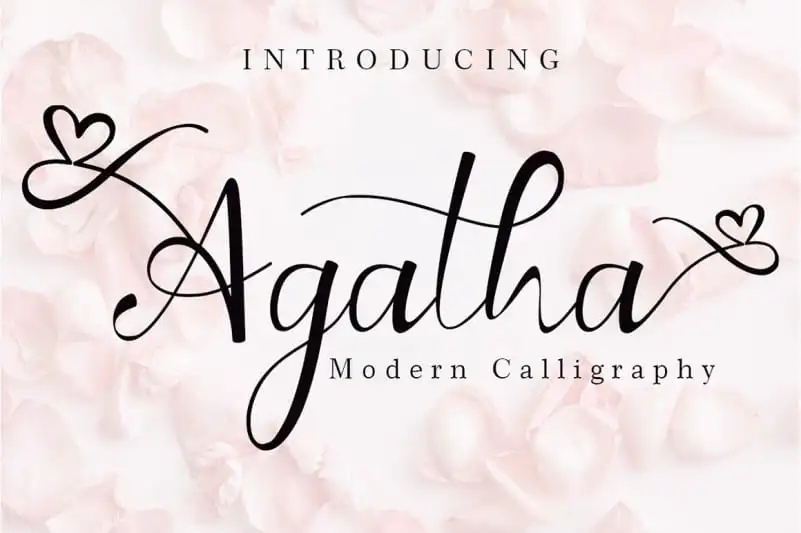
Agatha Calligraphy Font – Download Grátis
A Agatha Calligraphy Font é uma bela e elegante fonte moderna para escrita feita à mão. Esta fonte se destaca não apenas por sua beleza, mas também pela sua versatilidade. Ela serve perfeitamente para projetos que exigem um ar de romance e romantismo, como convites de casamento ou planos de evento, onde é importante criar uma atmosfera íntima e delicada. Além disso, a Agatha Calligraphy Font é um recurso valioso para quem deseja destacar seus produtos. Ela ajuda os artistas em marketing a comunicar suas ideias de maneira encantadora e persuasiva. A fonte também é ideal para capturar momentos preciosos durante férias, ou mesmo para aqueles que desejam expressar sentimentos especiais através das redes sociais. A Agatha Calligraphy Font não só oferece uma sensação de elegância, mas também é uma ferramenta poderosa para quem deseja transmitir emoções e personalidade através da escrita feita à mão. Se você está em busca de um recurso gráfico que capte o encanto do amor ou a celebração dos momentos especiais, esta fonte é perfeita.